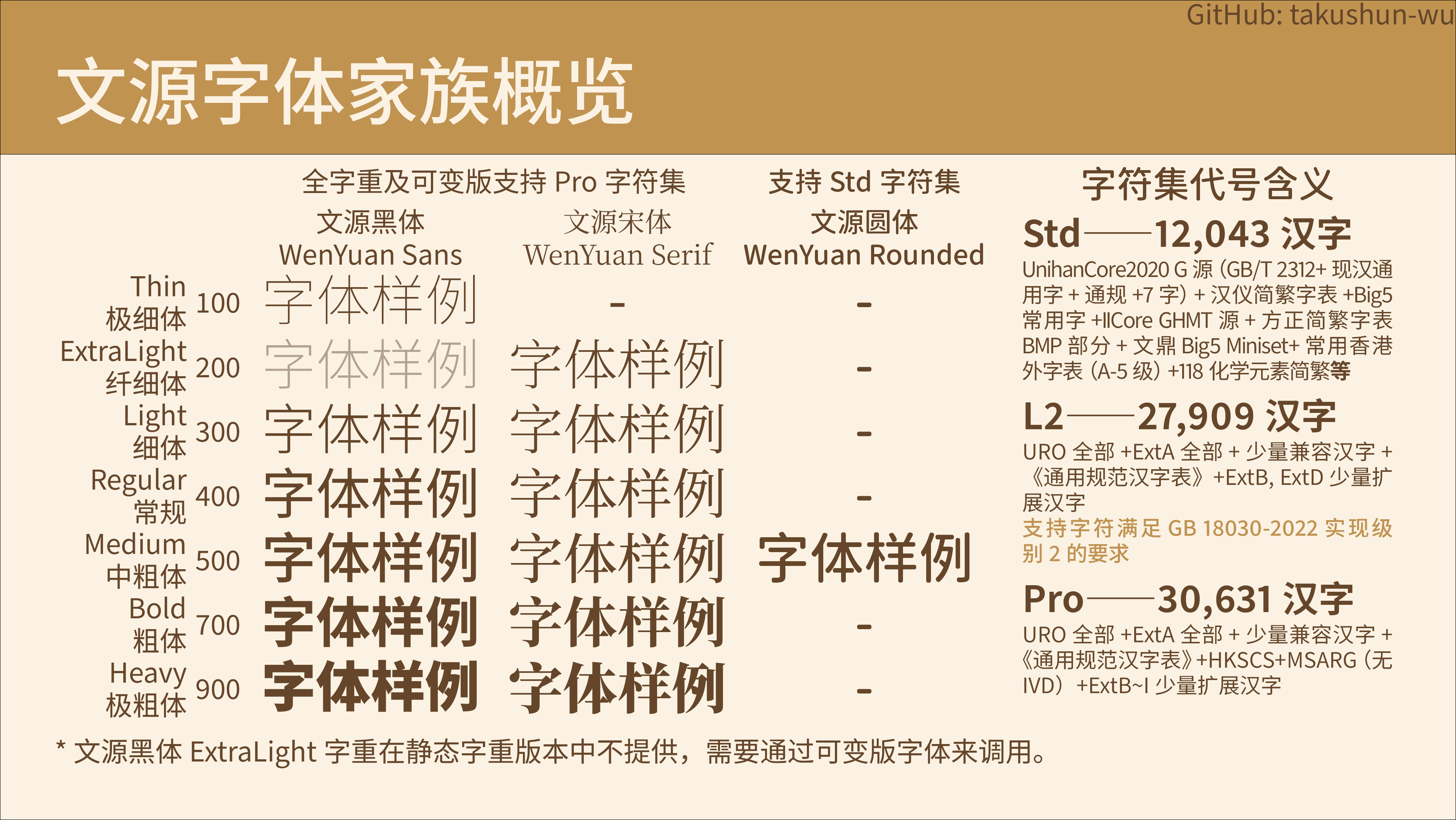
文源字体(预览版)
基于思源字体进行二次开发,使之更加适合在简体中文情景下使用以及简体中文TeX排版领域的中文字体,开源免费商用。
简介
文源字体包含三大字体系列:文源黑体、文源宋体和文源圆体。这些字体都是基于思源黑体和思源宋体二次开发而来。文源字体支持的大多数汉字(GB 18030-2022实现级别2范围内几乎全部)采用中国大陆字形标准,且非汉字符号迎合简体中文一般使用习惯。以上字体均采用OFL协议,任何个人与团体均可免费商用。
虽然Adobe和Google联合发布的思源黑体和思源宋体对整个东亚的设计和出版领域起了十分重大的影响,同时也开启了基于中日韩文字的开源字体的新局面,但囿于单个字体文件的65,535字形数限制等技术原因,同时还要支持中国大陆、港台地区、日本、韩国等多个区域的字形显示,因此某个地区版本的字体有时会出现不符合该地区字形标准的现象。
文源字体针对以上弊病,对原版思源字体进行优化,改正了错误汉字字形。为减少不必要的空间消耗,移除了原版思源字体的多地区字形支持。同时还根据实际使用需求,增加了一定数量的扩展区汉字(扩展B~I)。此外还在原版基础上增加了西文字符、拉丁文斜体等功能支持,并在此基础上,新增一个字体家族——文源圆体。